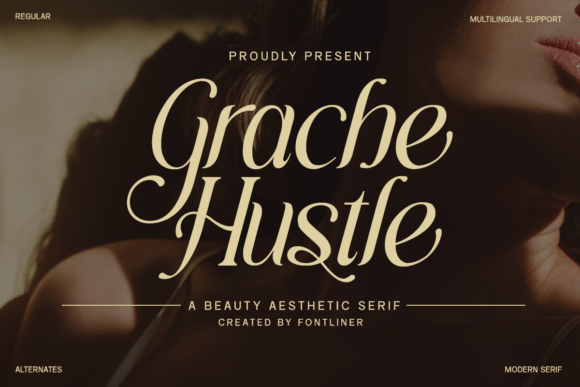
Grache Hustle
適切なデザイン要素を見つけるのは難しい場合がありますが、Grache Hustleは作品を即座に引き立てる優れたコレクションを提供します。
POD(オンデマンド印刷)製品、結婚式の招待状、またはソーシャルメディアのグラフィックを作成している場合でも、Grache Hustleは理想的です。